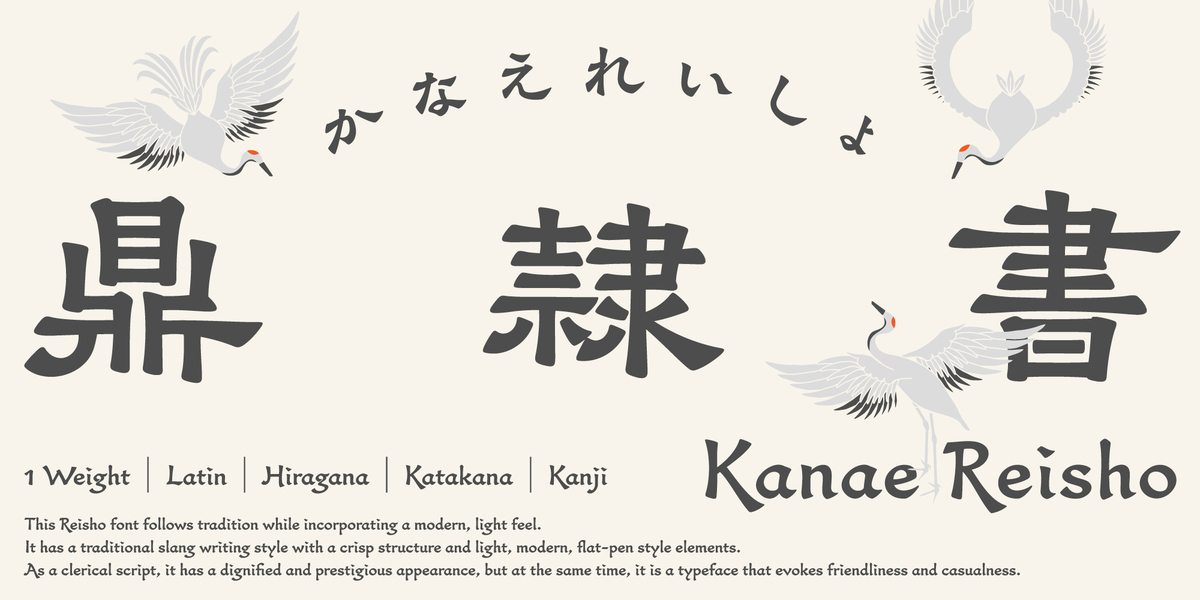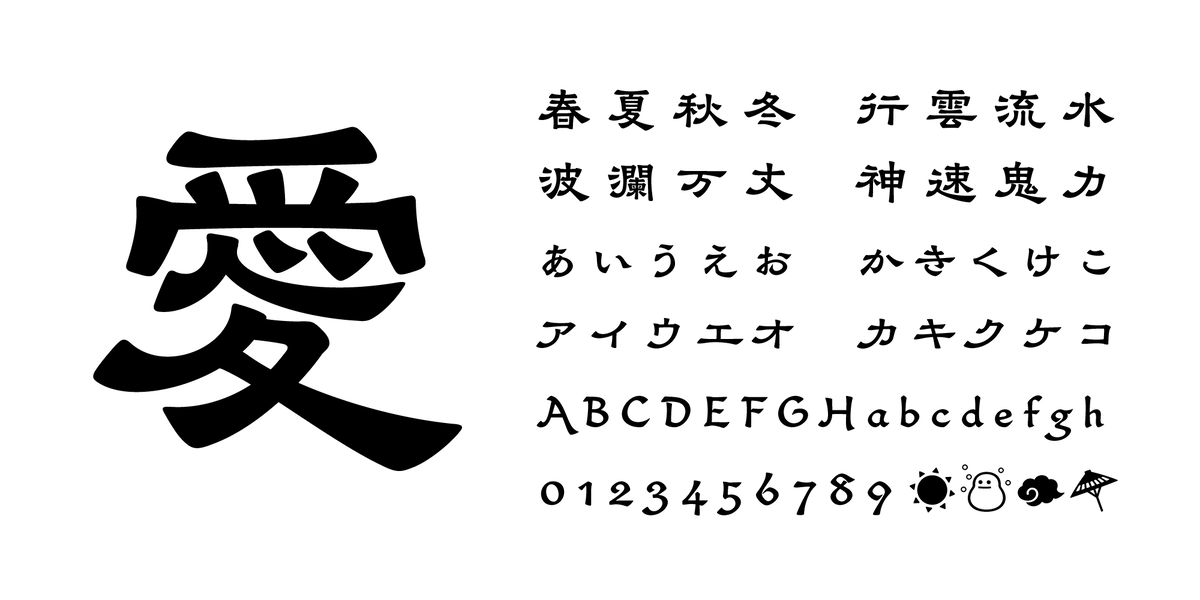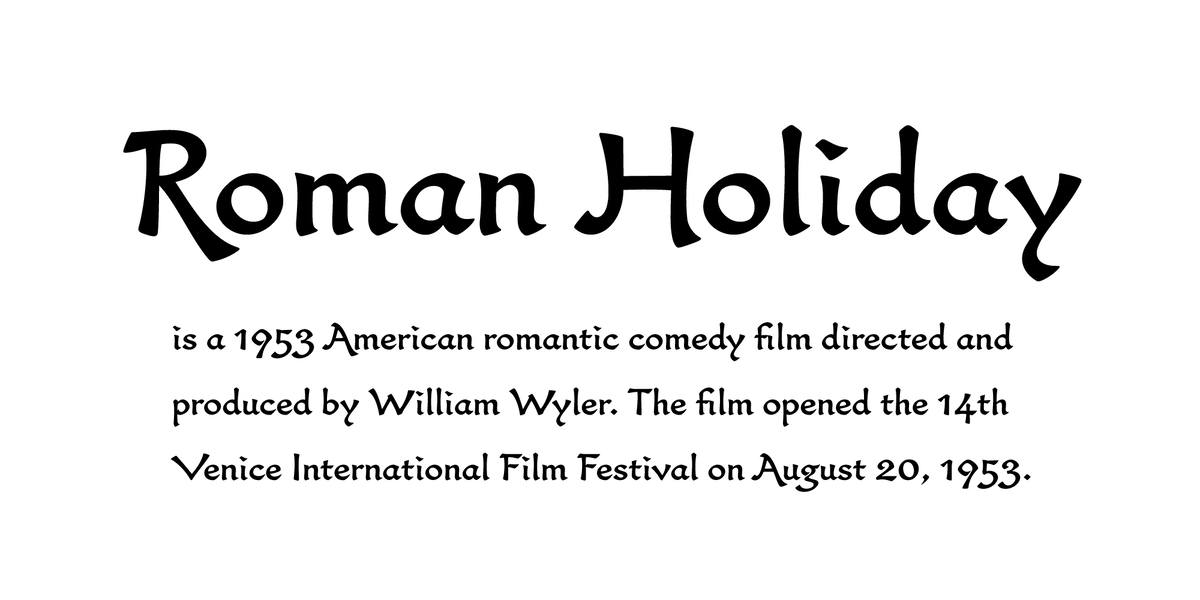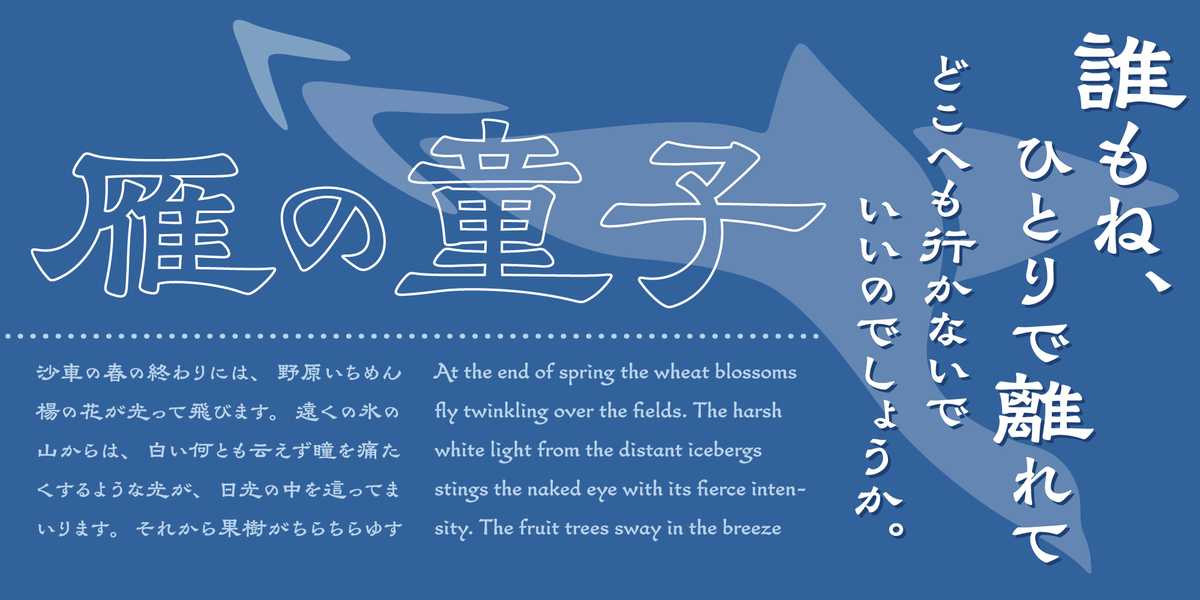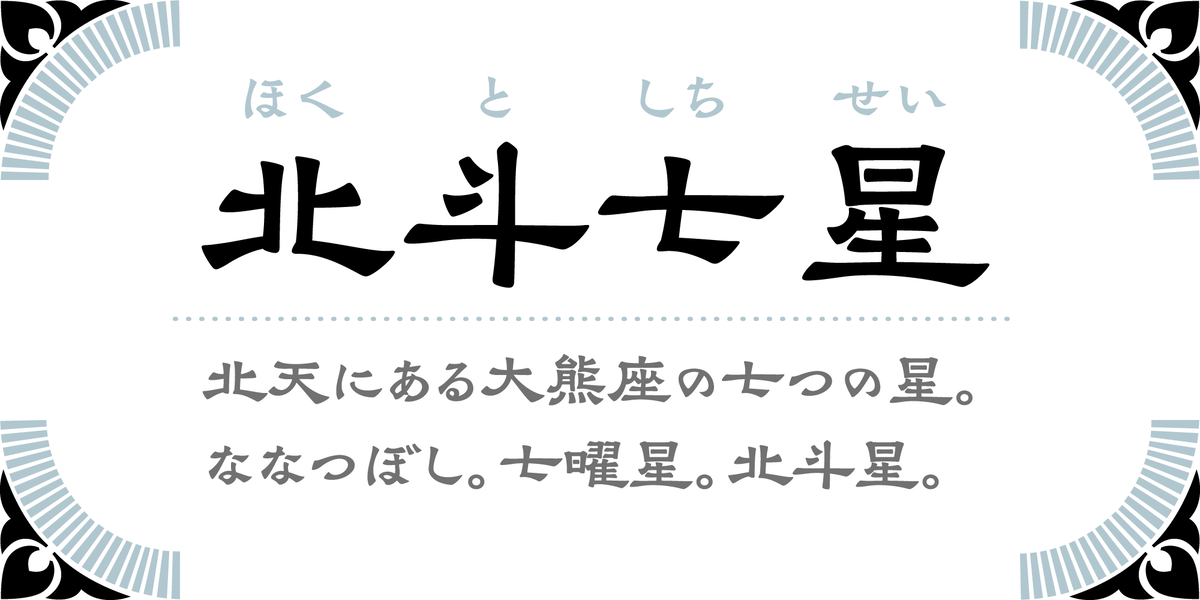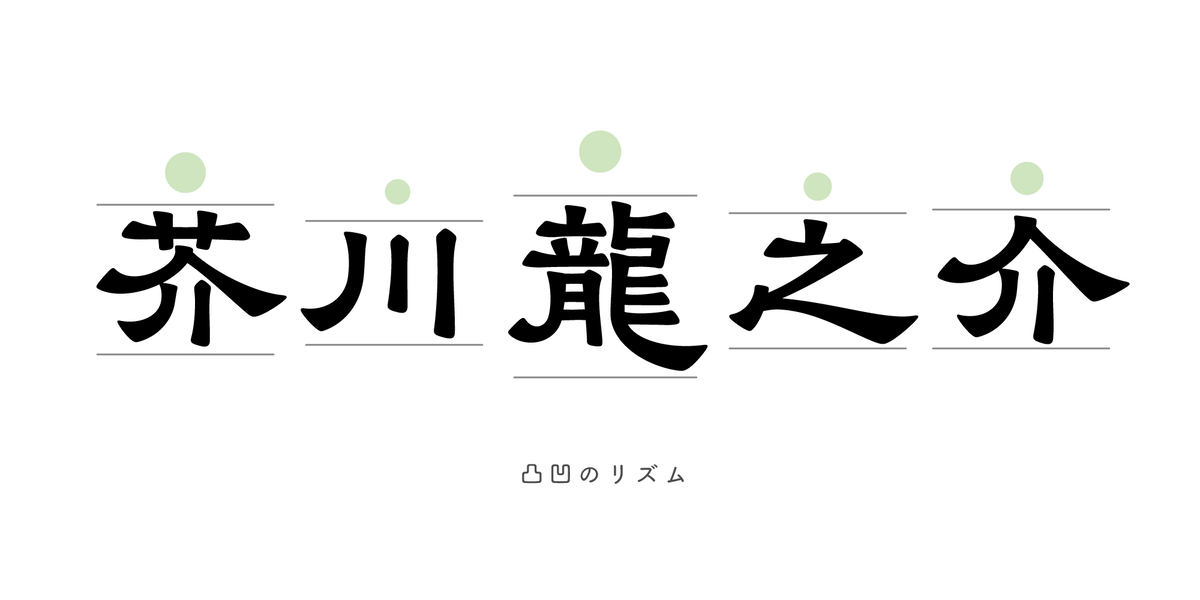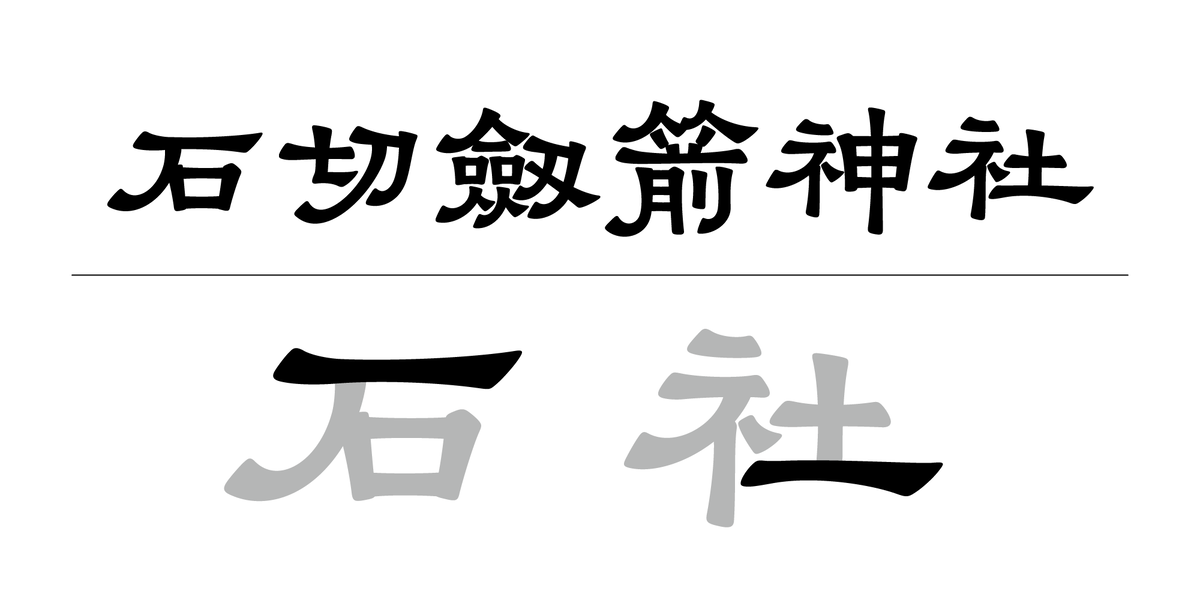
フォントワークスが初となるオリジナル隷書体「鼎隷書(かなえれいしょ)」を発表
フォントワークスは、2024年10月29日に伝統と革新が生み出す独自のリズム感による隷書の可能性を広げる新たなオリジナル隷書体「鼎隷書(かなえれいしょ)」をリリースした。
フォントワークス2024年新書体「鼎隷書」
「鼎隷書Std B」は、フォントワークス書体デザイナー・山村佳苗氏による当社初のオリジナル隷書体。
伝統を踏襲しながらも現代的な空気をまとった隷書体であり、歴史的な筆法に添いながらも、メリハリのある骨格と軽やかな平ペン風のエレメントで、リズミカルな形を楽しむことができ、書籍やパッケージ、テロップなど幅広いジャンルで活用でき、新たな可能性を秘めた隷書体となっている。
「鼎隷書」の特長
1.軽やかで現代的な空気を生むリズム感
通常デジタルフォントは正方形の枠内に文字を収めるが、当書体はその枠に囚われることなく、文字の本質を追求した新たな書体となる。
扁平(へんぺい)に描かれた部分や縦に強調された部分があり、文字ごとに明確なメリハリがあり、さらに、文章を組んだときにも背の高い文字と平たい文字が混ざり合うことで、独特でリズミカルな雰囲気が生まれる。
2.堅実なイメージを醸し出す波磔(はたく)
隷書の特性の「波磔(はたく)」と呼ばれる、うねった横の線や右ハライを特に強調している。
この特性は隷書の魅力を生み出し、深い歴史を醸し出す。
「鼎隷書」では、波磔を際立たせることで、現代的な雰囲気の中にも隷書の堅実さを結合したデザインを実現した。
▼波磔(はたく)の例